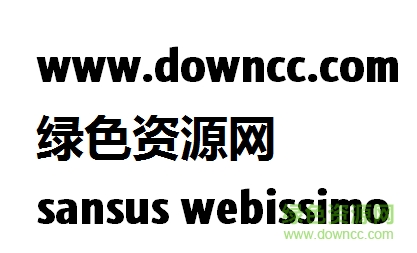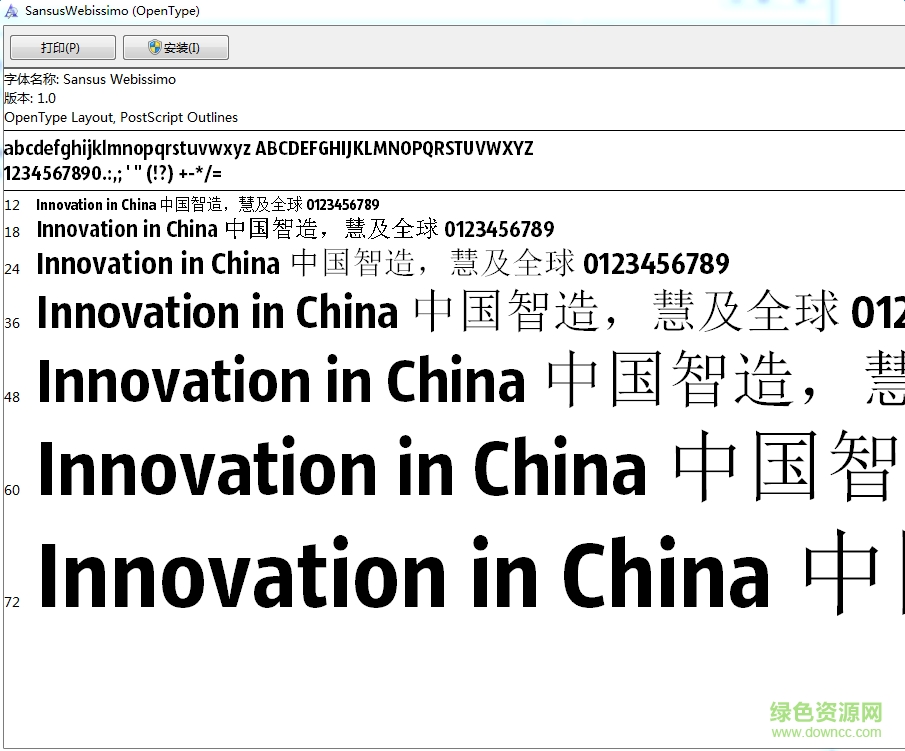
sansus webissimo字體是英文字體系列中經(jīng)典的一款英文無襯線字體,字形設(shè)計(jì)規(guī)范,線條變化自然,整體雅致美觀,可應(yīng)用于時(shí)尚雜志或宣傳海報(bào)等領(lǐng)域,綠色資源網(wǎng)還有更多免費(fèi)字體下載哦!
sansus webissimo字體是一款深受設(shè)計(jì)師喜愛的字體,此款字體具有一定的藝術(shù)感,易讀性非常強(qiáng),字體相對來說比較完整,應(yīng)用范圍比較廣泛,喜歡的朋友歡迎來綠色資源網(wǎng)下載收藏!